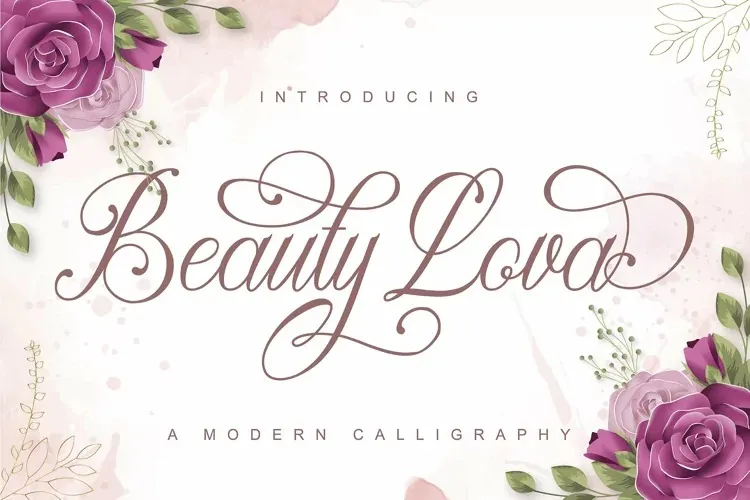
A fonte ‘Beauty Lova’ oferece uma experiência fluida e elegante para designers. Trata-se de um tipo tipográfico liso que evoca a caligrafia moderna, com linhas suaves e escritas manuscritas. Perfeito tanto para logotipos quanto para design de estação de wedding, cartões de felicitações, embalagens de produtos e mesmo para assinaturas de fotos ou marcaságens, a ‘Beauty Lova’ é uma escolha perfeita. Com seu amplo conjunto de swashes, que permitem aos designers adicionarem detalhes decorativos com facilidade em segundos, esta font não apenas oferece uma variedade única, mas também simplifica a criação de designs atraentes e elaborados. Como uma font PUA encodada, a ‘Beauty Lova’ é fácil de acessar todos os elementos mágicos e swashes que ela possui. Através desta fonte moderna e amigável, designers de todo o mundo podem expressar sua criatividade com elegância e sofisticação, tornando-a uma opção imprescindível para qualquer projeto visual.